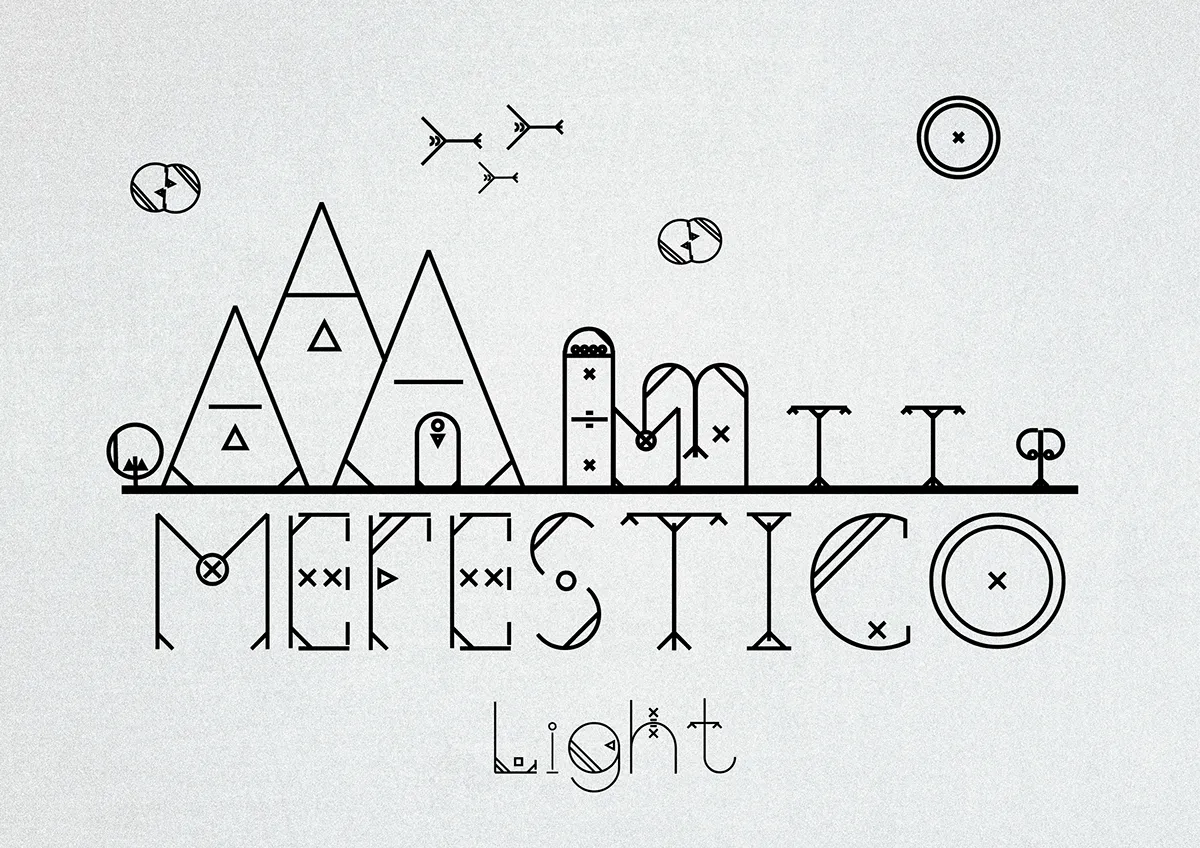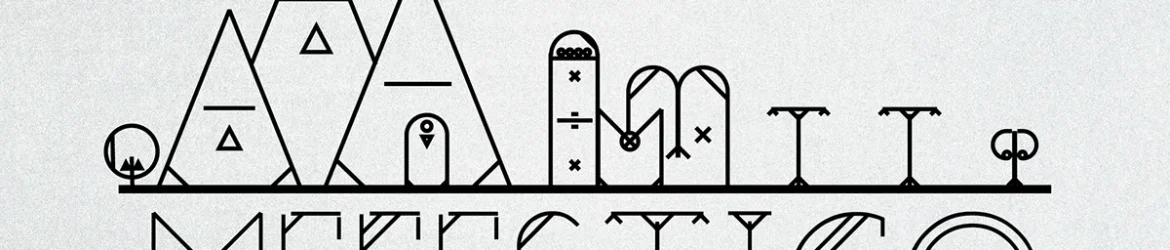
A Mefestico Font é uma tipografia decorativa que oferece uma experiência única para projetistas visuais do Brasil. Inspirada nas linhas sombrias e elegantes da literatura gótica, esta fonte se destaca por sua aparência sofisticada e versátil. Suas ondulações exuberantes tornam-a perfeita para adicionar um toque de brilho a qualquer projeto editorial, seja ele em revistas, sites ou editoriais de moda. O designer Hamilton criou uma obra-prima que combina elementos do gótico com um toque moderno e elegante. Perfeitamente adaptável para aplicativos digitais, também oferece uma versão manuscrita que permite a criação de uma aparência única em qualquer documento. A Mefestico é ideal para criar um layout moderno e sofisticado, mantendo o olhar voltado ao design gráfico brasileiro. Se você busca uma fonte com estilo marcante para dar vida à sua arte digital, a Mefestico Font é uma escolha inegavelmente atraente. Suas características únicas garantem que ela se destaque em qualquer projeto visual de alta qualidade.